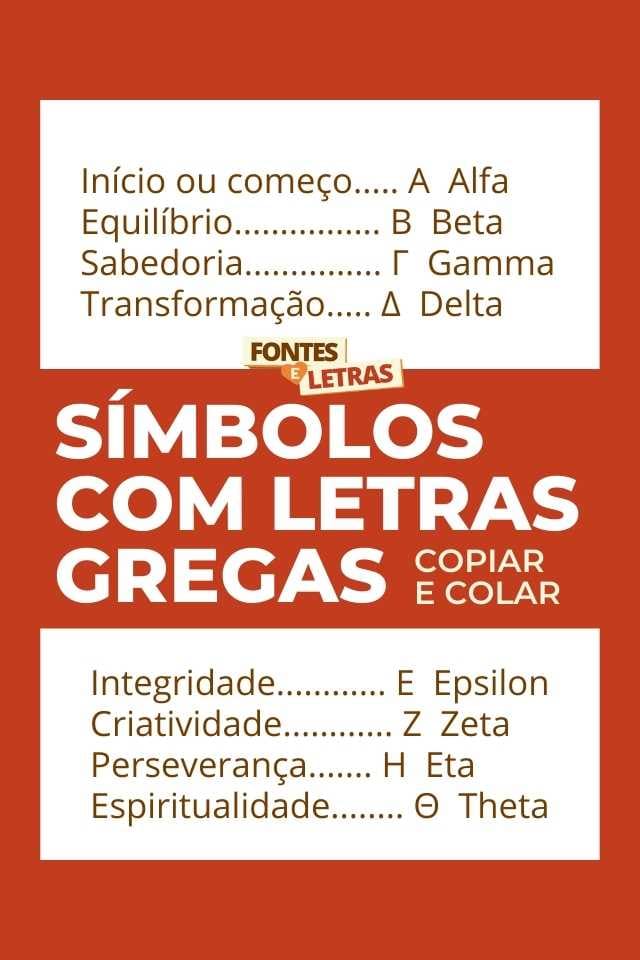
Letras Gregas para Copiar (Alfabeto Grego)
As letras gregas são caracteres para copiar e colar no nome, no nick, na bio ou como ideia de tatuagem. O alfabeto grego é a base de muitos símbolos usados até hoje na ciência e na matemática. Escreva o seu texto na caixa lá em cima pra ver o seu nome no estilo grega, ou copie direto da tabela abaixo.
O que são as letras gregas?
As letras gregas formam um dos alfabetos mais antigos do mundo. Além do visual elegante para nicks e tatuagens, várias letras (α, β, π, Ω) são símbolos famosos na matemática e na ciência.
💡 Dica: letras como Ω, Δ e π são muito usadas em nicks e logos por causa do visual forte.
Tabela do alfabeto grego
Equivalência aproximada entre as letras latinas e as letras gregas:
| Latina | Grega | Latina | Grega |
|---|---|---|---|
| A | α | N | ν |
| B | β | O | ο |
| C | χ | P | π |
| D | δ | Q | θ |
| E | ε | R | ρ |
| F | φ | S | σ |
| G | γ | T | τ |
| H | η | U | υ |
| I | ι | V | ω |
| J | ξ | W | ω |
| K | κ | X | χ |
| L | λ | Y | ψ |
| M | μ | Z | ζ |
Como usar as letras gregas
Usos das letras gregas
- Tatuagem — teste como fica a frase antes de tatuar (veja fontes para tatuagem).
- Nick e perfil — um nome diferentão nos jogos e redes.
- Decoração e arte — posts, convites e desenhos.
Perguntas frequentes
Como escrever o meu nome em grego?
Use a tabela de equivalência acima. Lembre que é uma aproximação visual entre o nosso alfabeto e o grego.
Posso usar as letras gregas em nicks e logos?
Sim, são muito populares. Letras como Ω, Δ e Σ dão um visual forte ao nick.